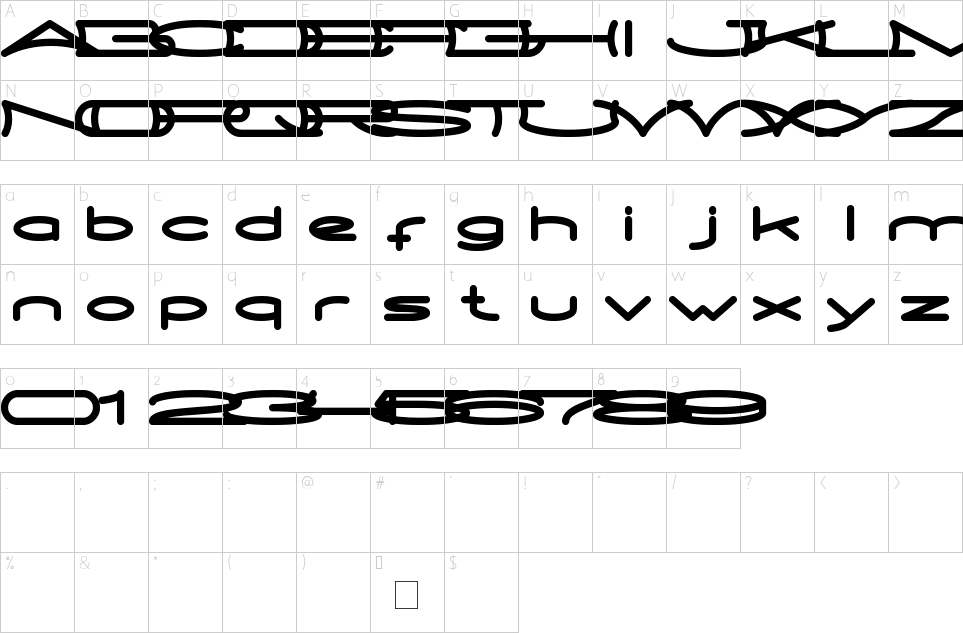
Metro City é uma fonte moderna e elegante projetada para dar um toque único a qualquer projeto digital. Com linhas leves e uma tipografia minimalista, Metro City é perfeita para aplicações de escrita informativa, logotipos de marcas modernas ou designs de websites. Esta fonte foi criada por um designer desconhecido, mas a sua beleza e simplicidade tornam-na um recurso gráfico indispensável. Metro City já foi baixada 7.152 vezes, demonstrando a sua popularidade e qualidade. Para quem está procurando por uma fonte clara e minimalista, Metro City é uma ótima escolha, garantindo um visual atraente em qualquer projeto.